Hiroyuki Matsuishi 1965年生于福冈,是一名日本平面设计师,在日本福冈九州产业大学获得了设计学学士学位。他是日本字体协会的成员,并建立了自己的设计办公室,专门设计品牌徽标、包装 、广告等。
今天跟大家分享他的字体作品,都是字形或创意较为突出的作品,希望这些作品能给大家带来灵感。一起来看看。
品牌字体微标设计
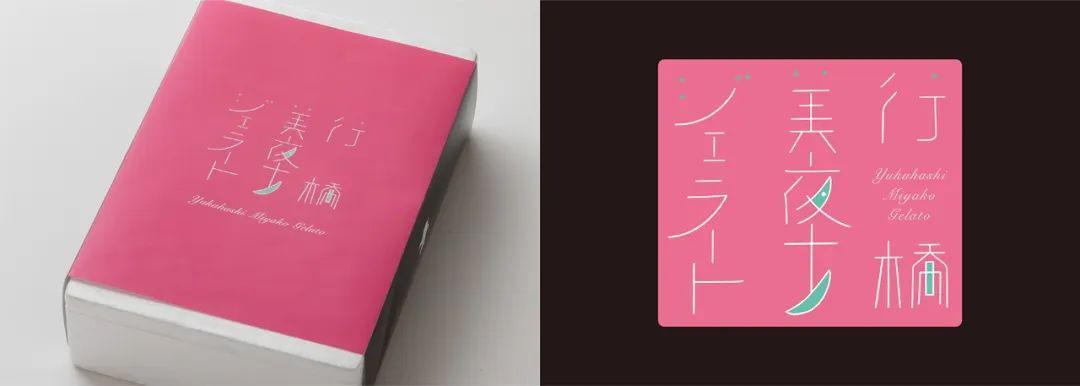
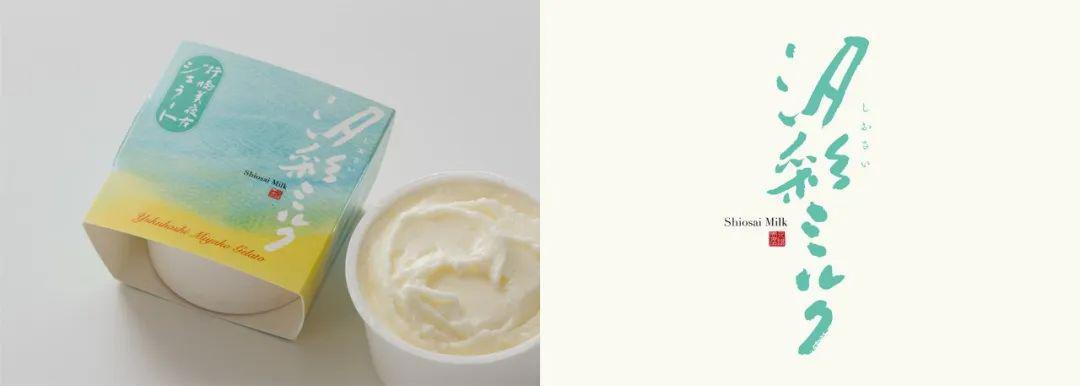
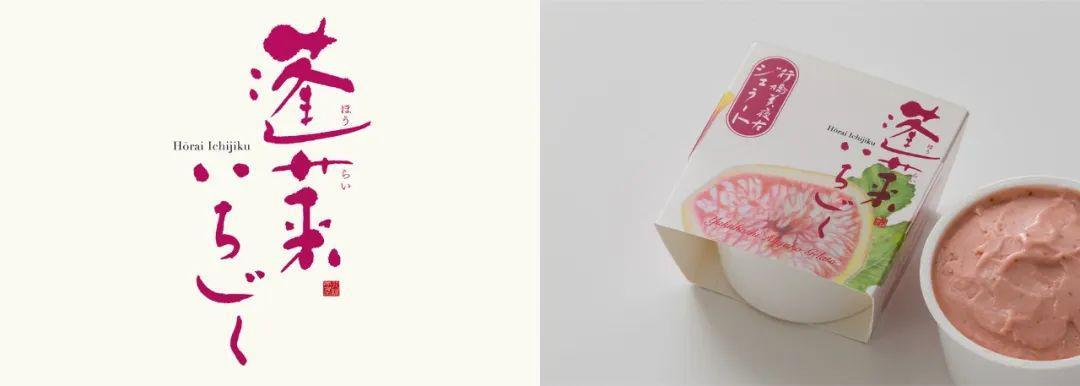
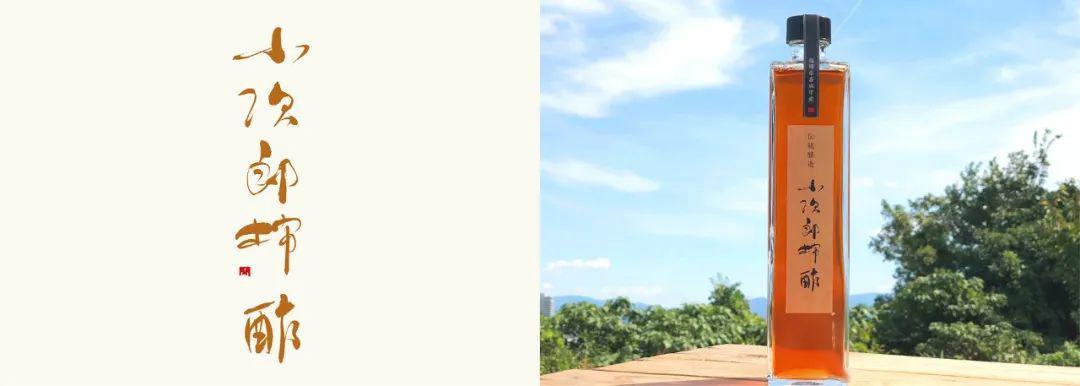
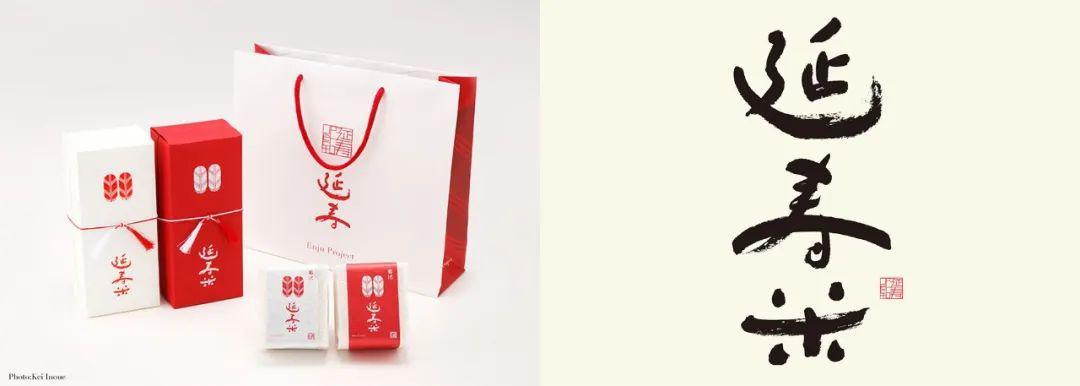
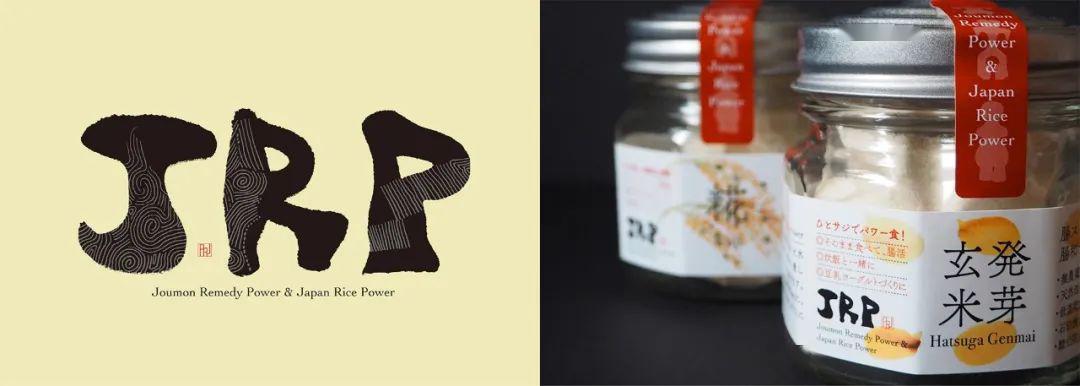
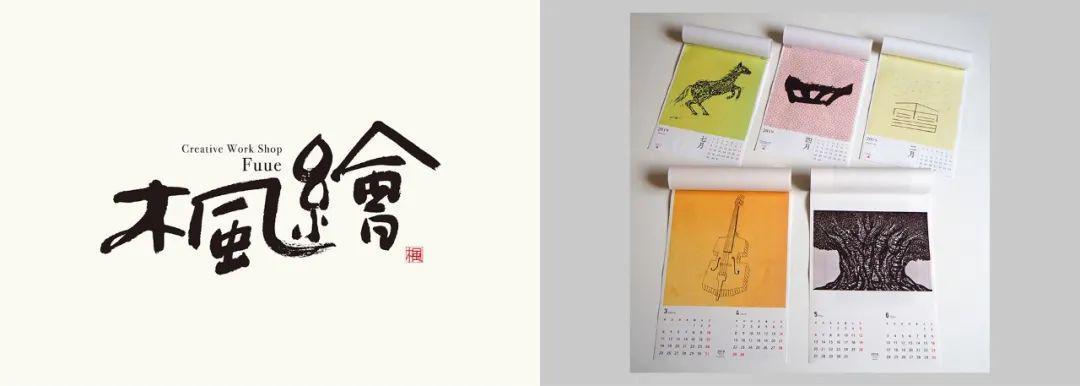
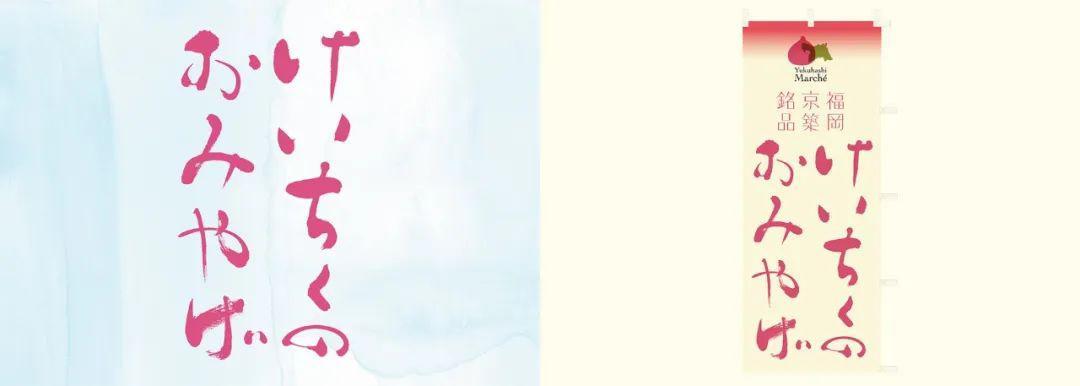
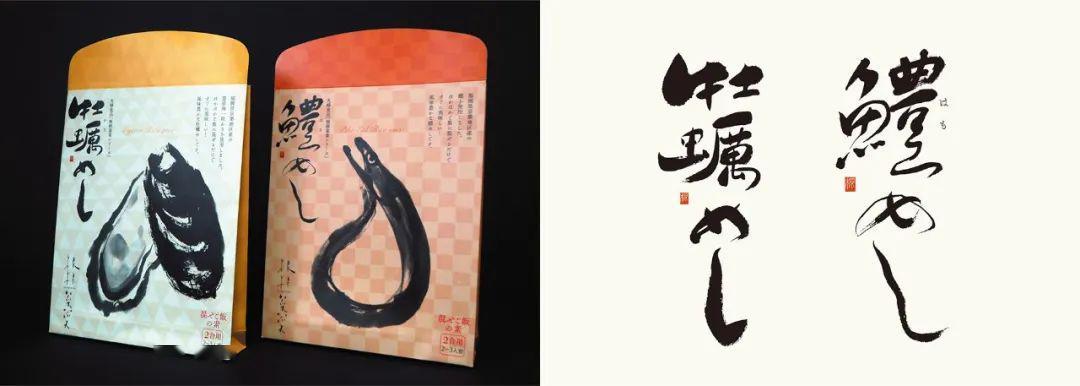
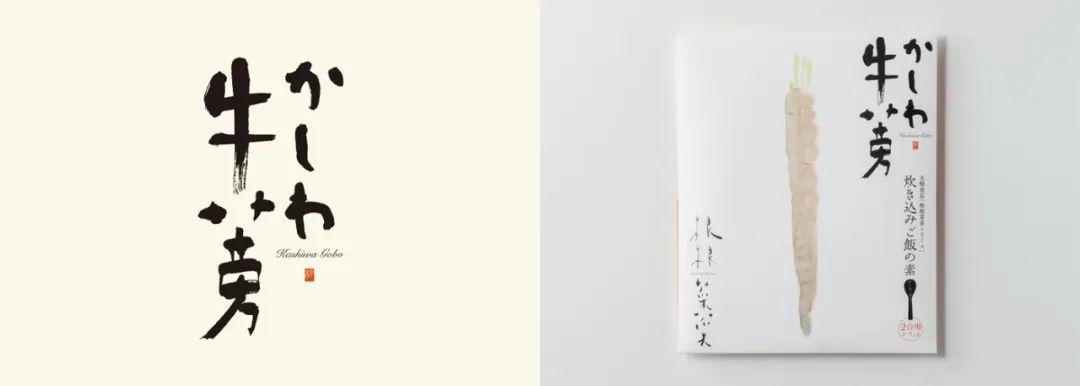
“象形字”LOGO设计
创意字形设计